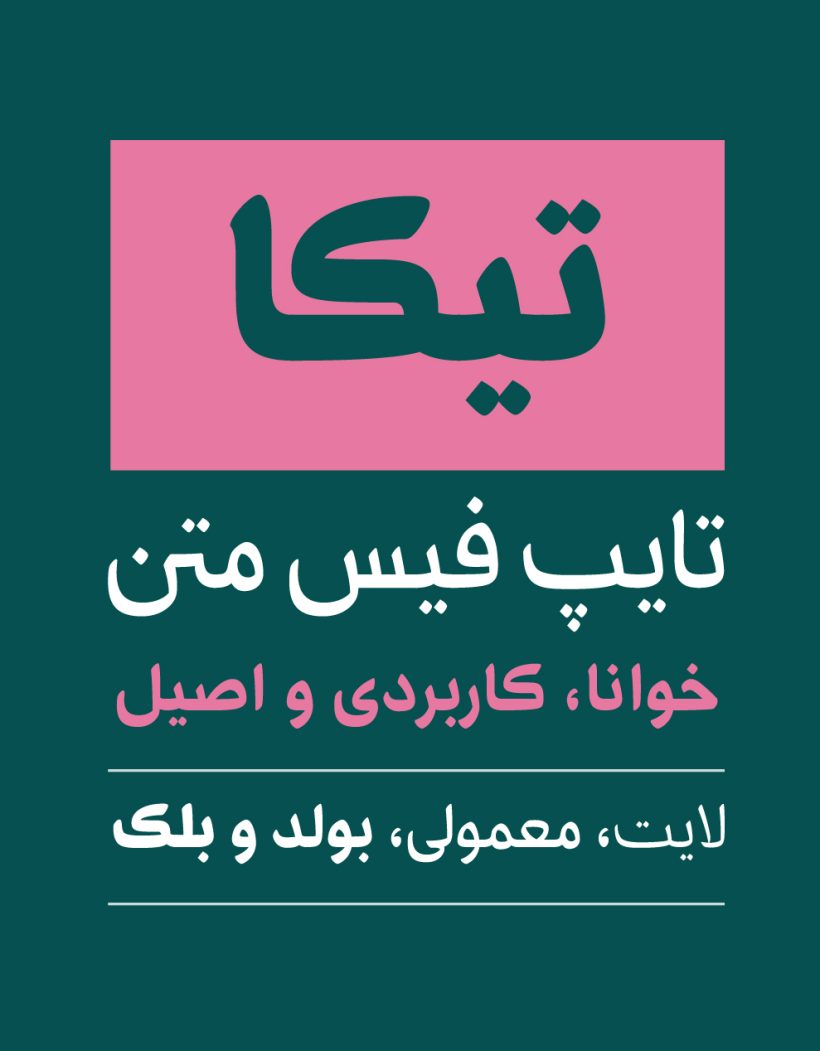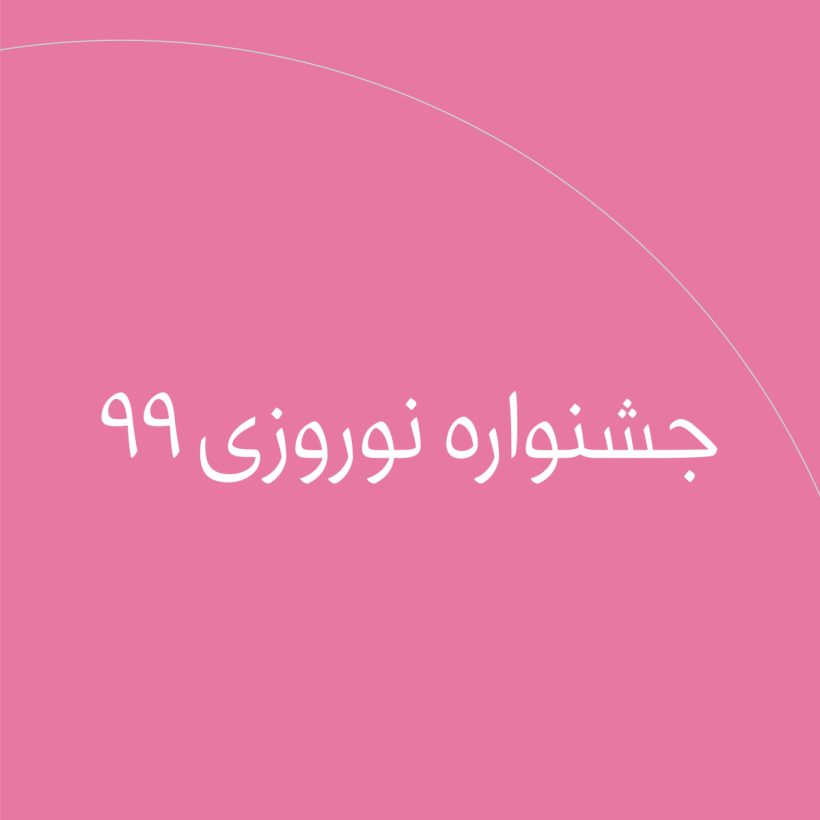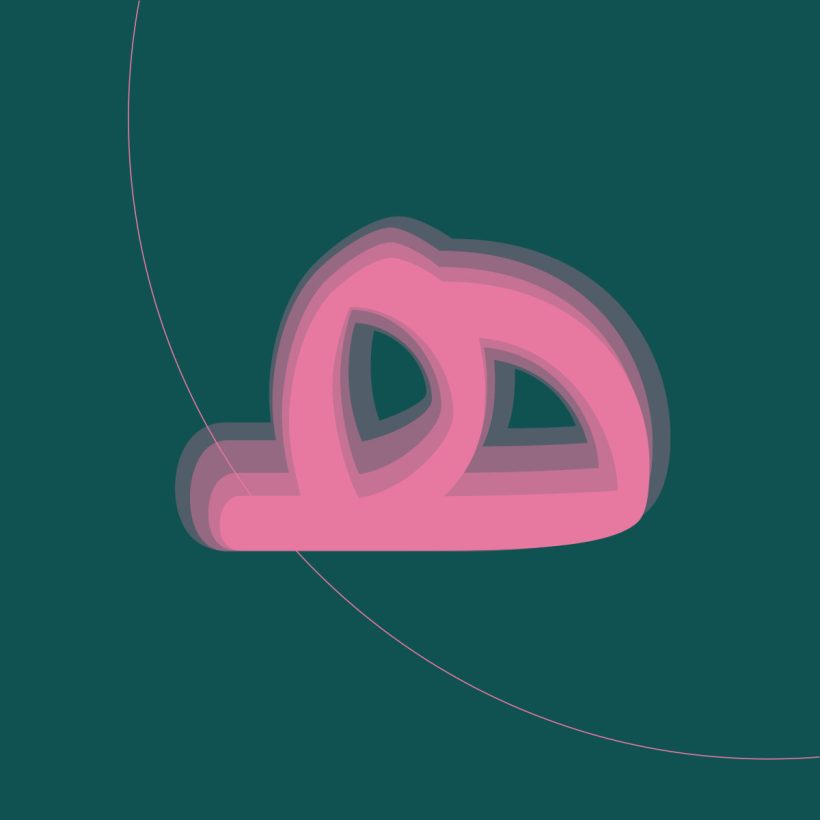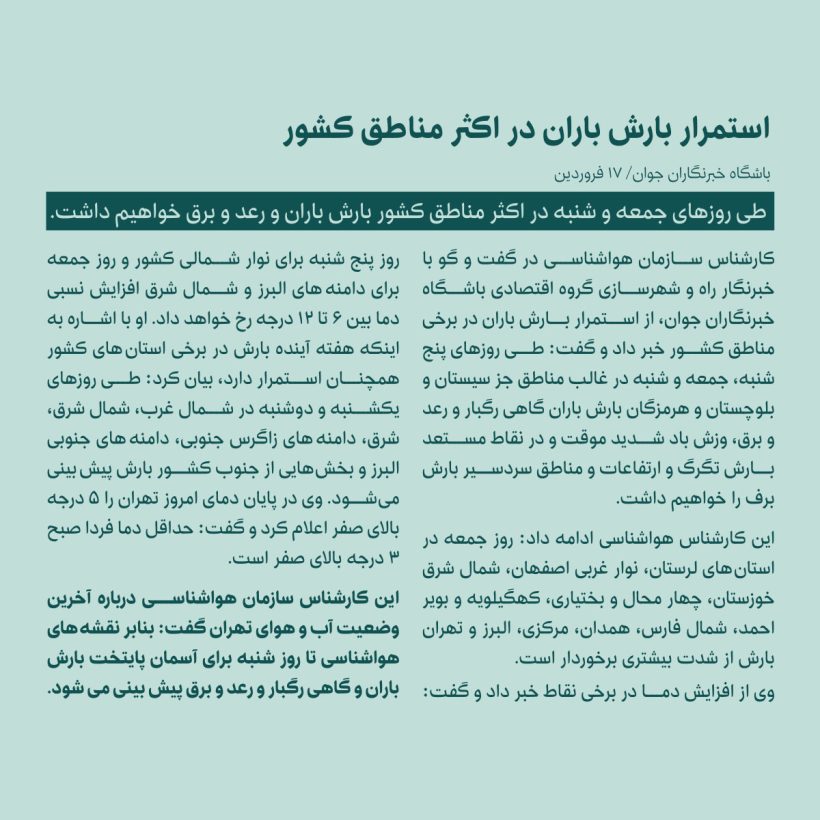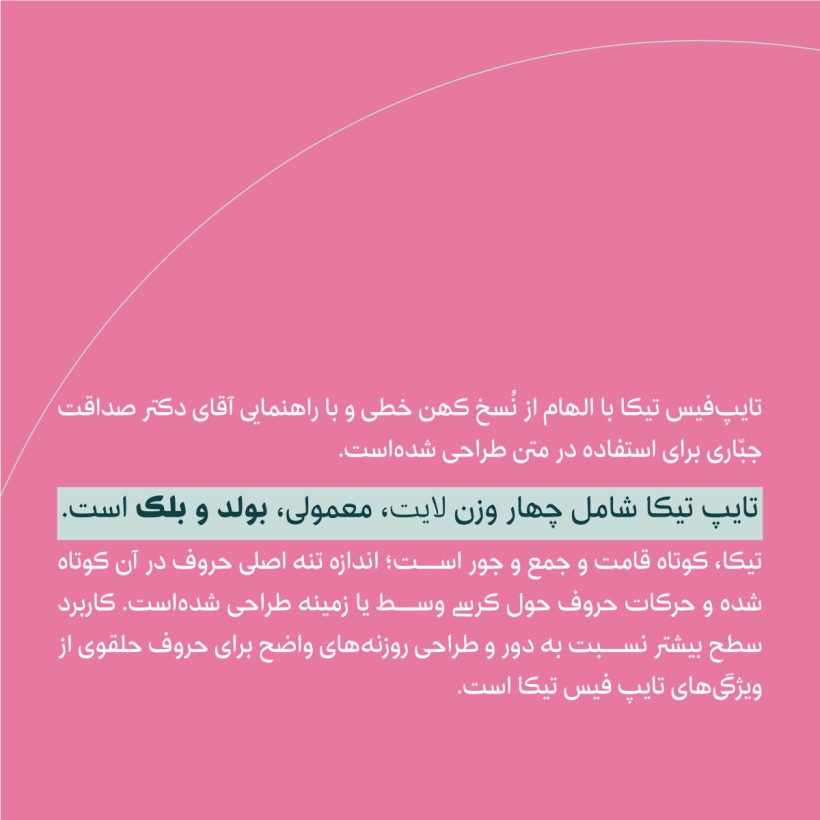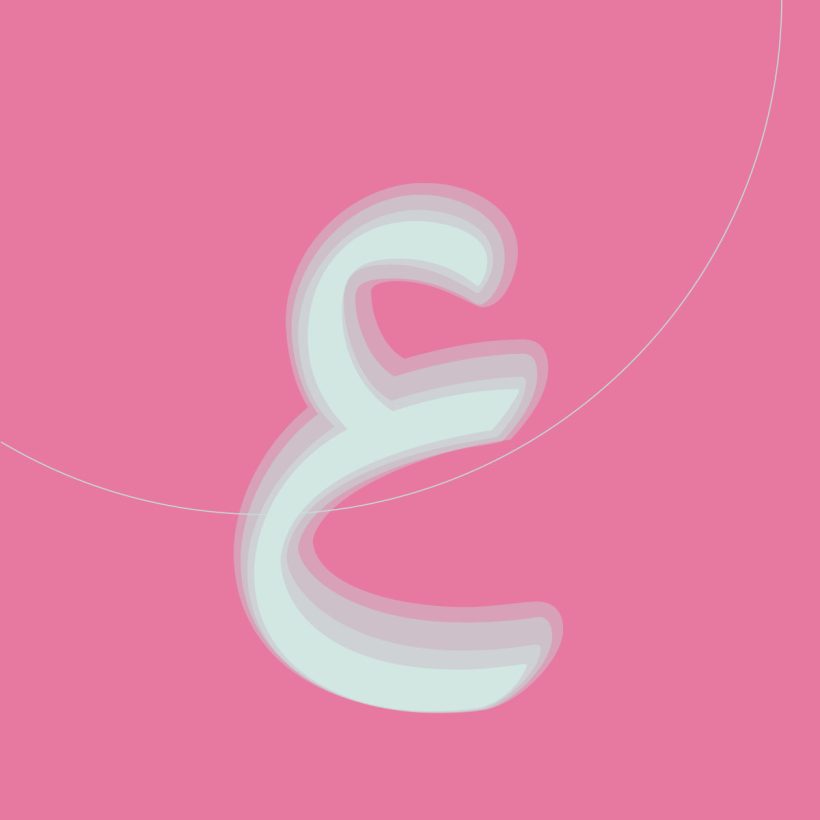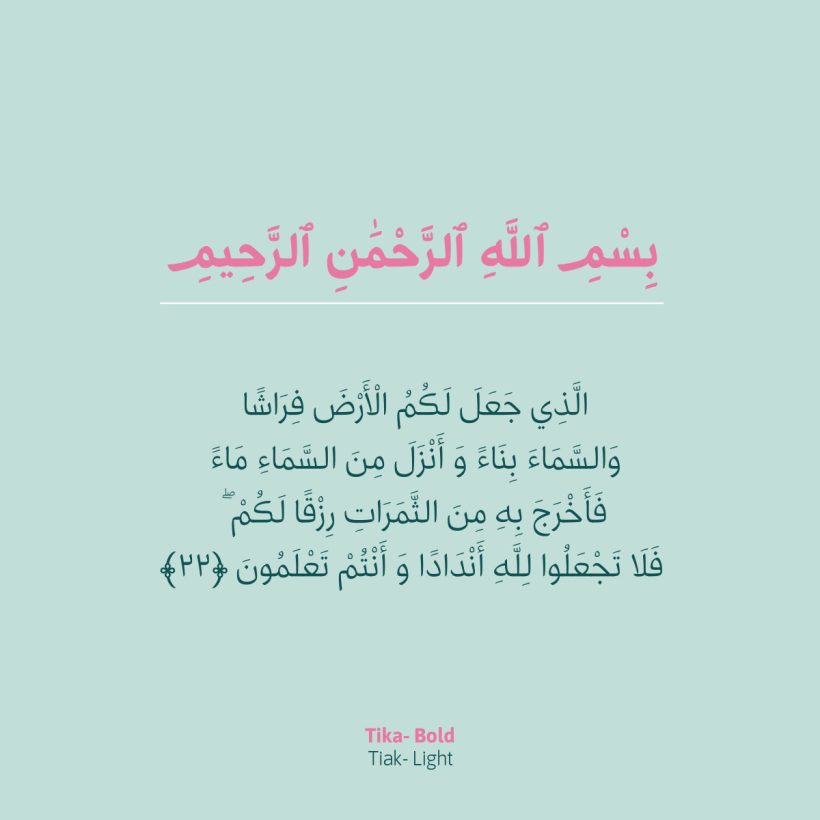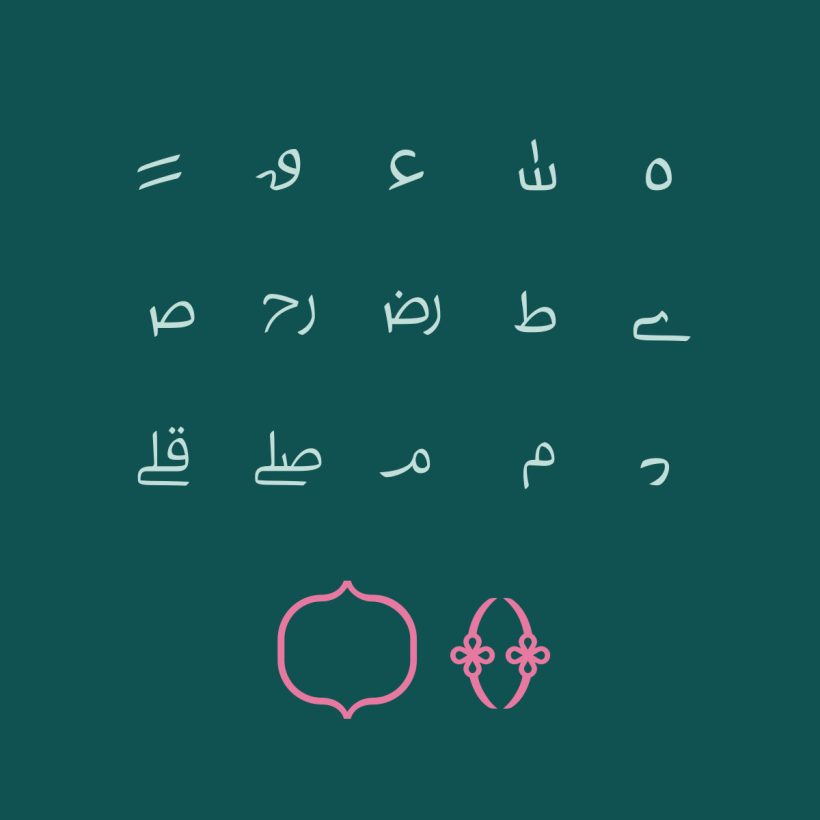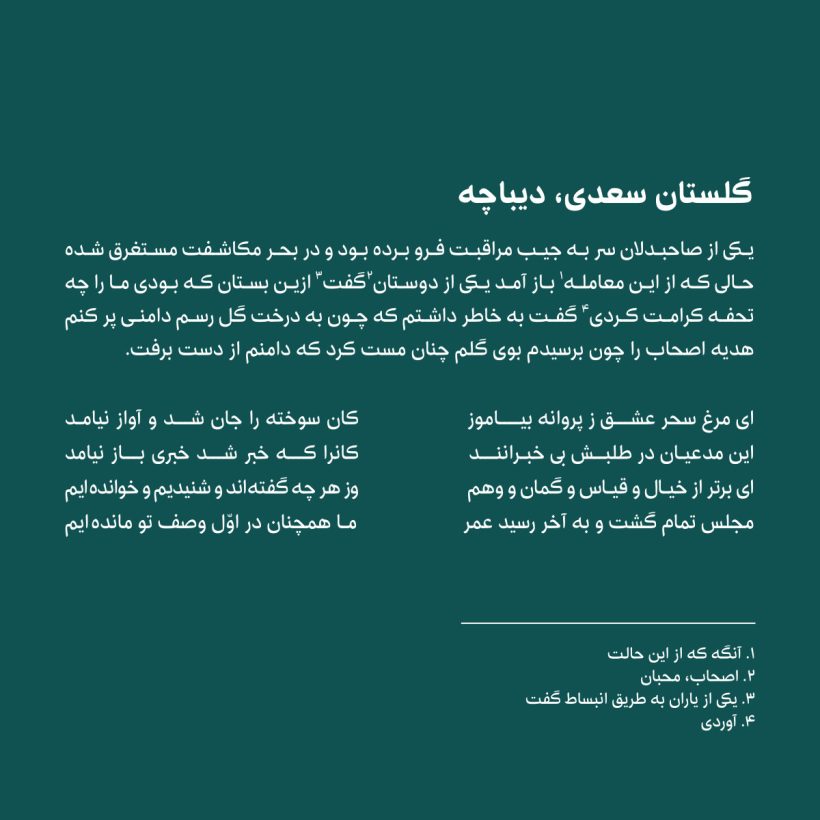
خانواده فونت تیکا
نیاز به فونت های خوانا، اصیل و کاربردی همواره برای کاربران فونت فارسی حائز اهمیت بوده و یکی از راه های طراحی فونت بهره گیری از خطوط نسخه های خطی و دخل و تصرف در اجزای حروف است مانند دخل و تصرف در حروف حلقوی و روزنه ها. اما نکته مهم رعایت اصل تناسبات حروف است و تغییر در روزنه های بایستی تا حد امکان با رعایت این اصل صورت گیرد خصوصیتی که تا حد ممکن در فونت تیکا رعایت شده است.
تیکا تایپ فیس متن است و با الهام از نسخ کهن خطی و با راهنمایی آقای دکتر صداقت جباری طراحی شده است. تیکا شامل چهار وزن لایت، معمولی، بولد و بلک است. تیکا، کوتاه قامت و جمع و جور است؛ اندازه تنه اصلی حروف در آن کوتاه شده است و حرکات حروف حول کرسی وسط یا زمینه طراحی شده که دید بیننده را به این بخش از فونت معطوف کرده است. کاربرد سطح بیشتر نسبت به دور و کنتراست متعادل پهنا و نازکی حروف از ویژگی های تیکا است؛ خصوصیتی که سبب ایجاد خاکستری متعادلی در متن و خوانایی فونت شده است. یکی دیگر از ویژگی های تیکا، وزن بلک آن است که در کنار وزن لایت، برای نوشتن عناوین کوتاه و امور تبلیغاتی می تواند مناسب باشد. قواعد کرنینگ و اعراب گذاری ها در فونت تیکا اعمال شده است. تیکا دارای لیگیچر و کارکترهای جایگزین است تا برحسب نیاز و برای زیبایی بیشتر به کار گرفته شود.
فونت انگلیسی Asap متناسب با لحن تیکا انتخاب شده و در آن جایگذاری شده است.
اعداد فارسی و عربی در فونت تیکا تنظیم شده و قابل استفاده است.